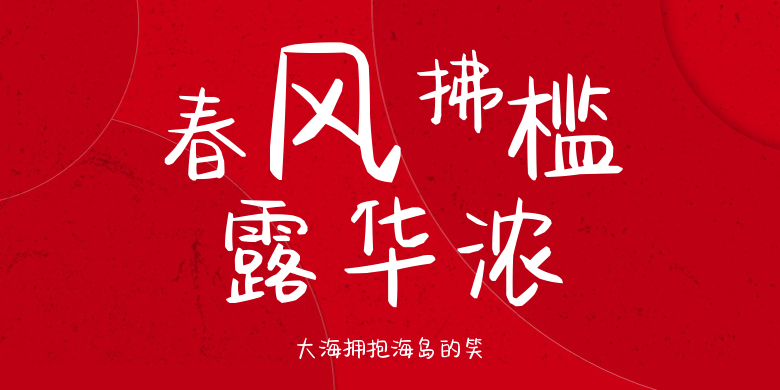
大海拥抱海岛的笑
大海拥抱海岛的笑,这款字体结构工整、笔画清晰,兼顾美观与易读性,适用于标题、正文、海报、包装、LOGO 等多种场景。字形优雅稳定,风格百搭耐看,适配日常排版与创意设计,让文字呈现更舒适、更具质感。大海拥抱海岛的笑一笔一画,皆是细节,以均衡的比例、流畅的线条打造舒适视觉体验,字形端正大气,风格简约现代。无论是商业设计、品牌宣传还是日常排版,都能轻松驾驭,让文字更有格调与力量。大海拥抱海岛的笑字体下载。